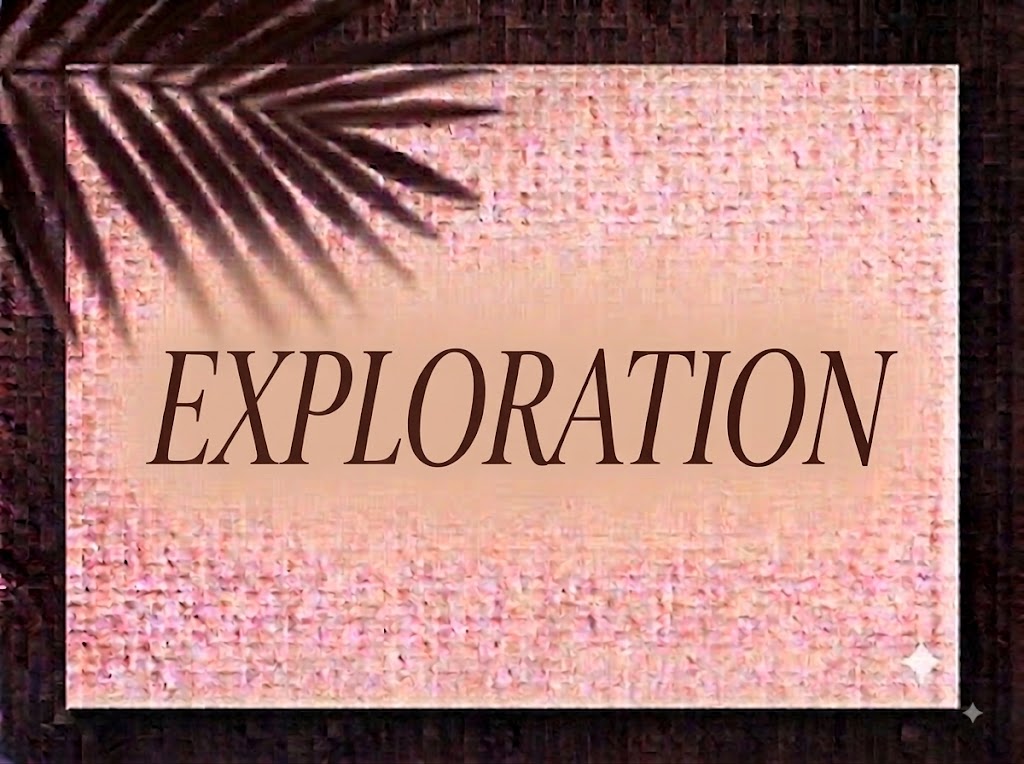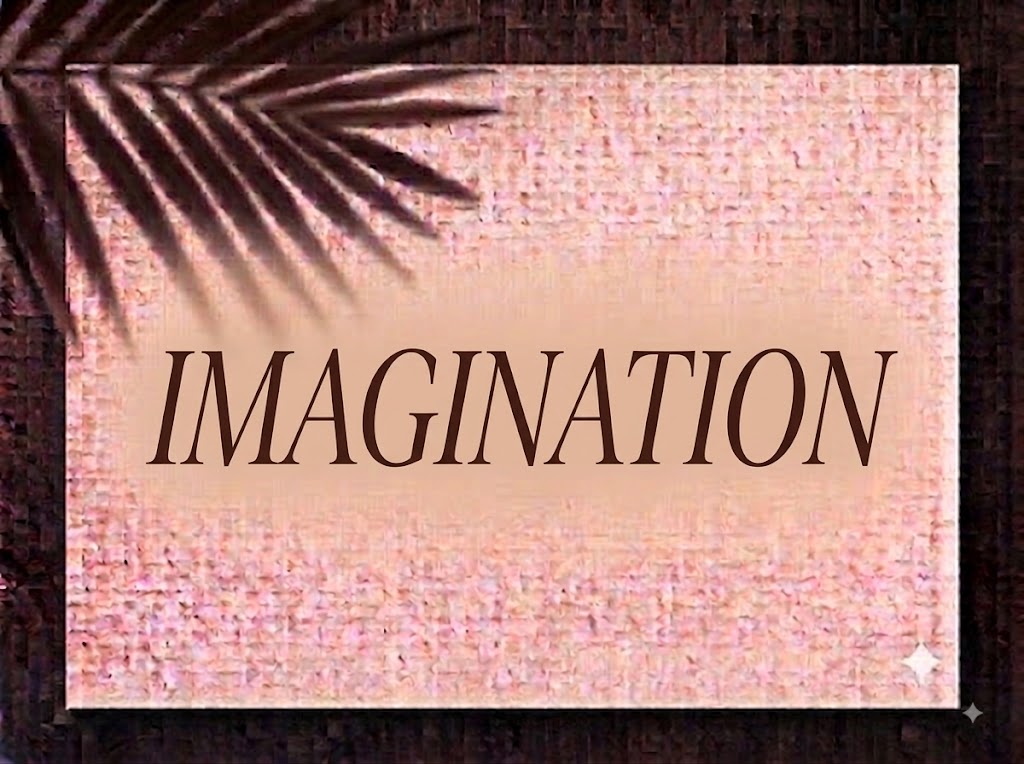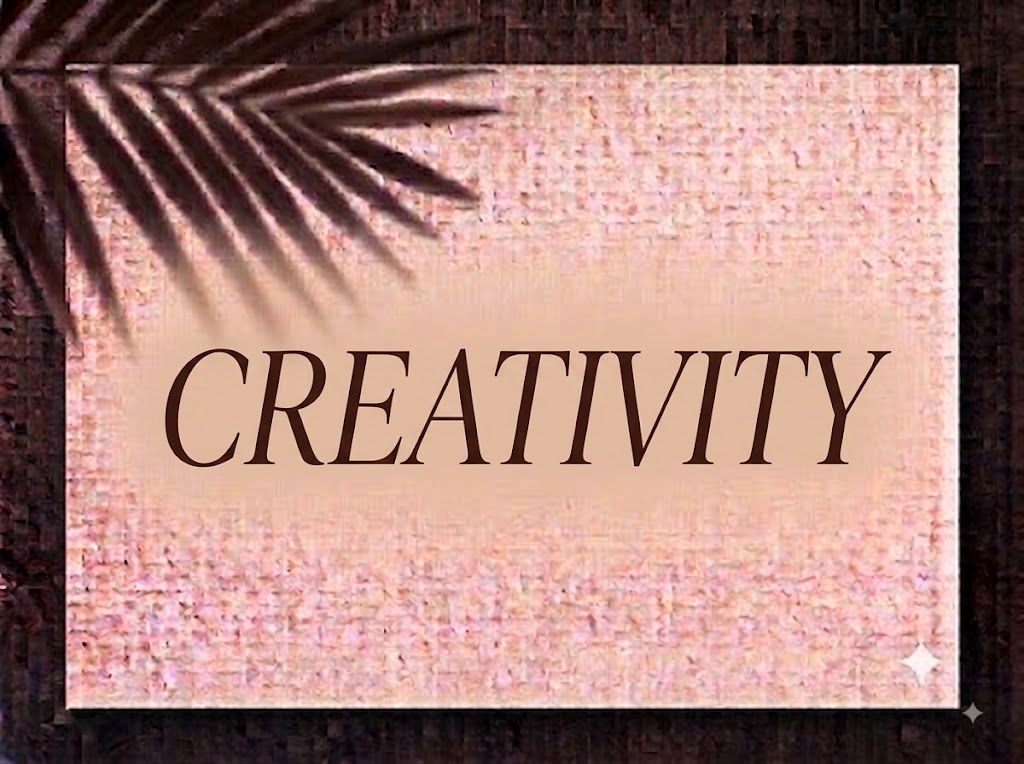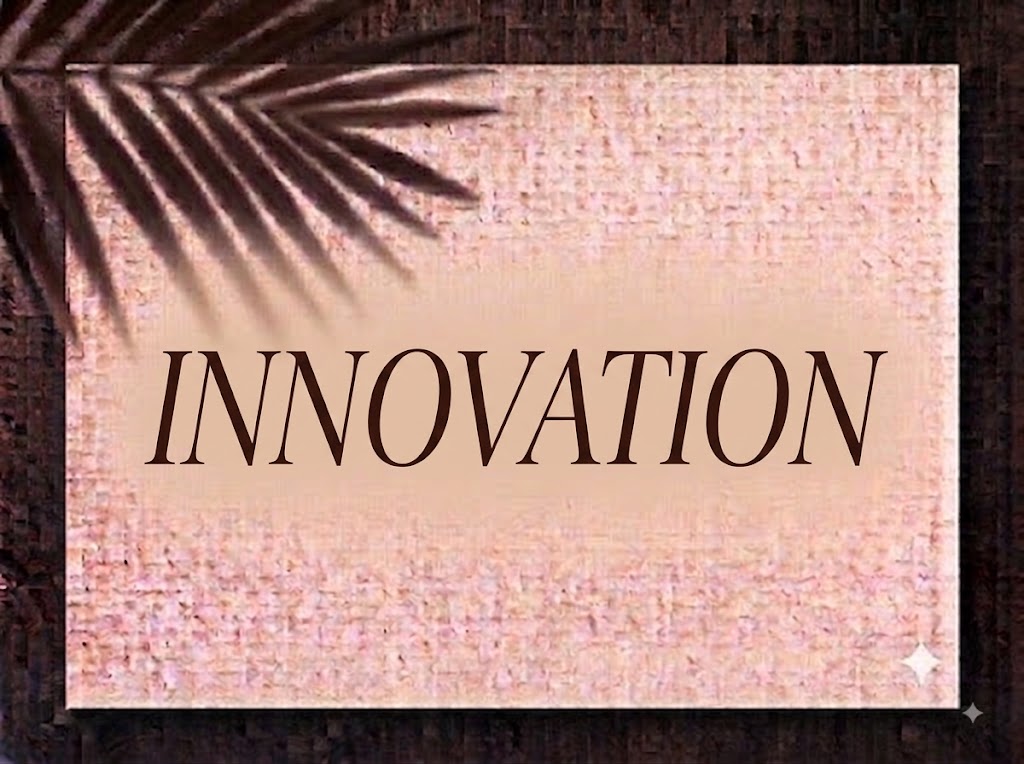
1FTV VIP Ameng
Trong ngành thiết kế đồ họa truyền thông cao cấp, thời trang và xuất bản Tạp chí (Editorial), những bộ chữ hiển thị (display serif) sở hữu đường nét kiêu sa cùng các chi tiết uốn biến điệu độc đáo luôn mang đến sức hút thị giác vượt trội. Một tiêu đề được trau chuốt tinh tế không chỉ truyền tải trọn vẹn thông điệp mà còn nâng tầm đẳng cấp nghệ thuật cho toàn bộ ấn phẩm.
Nếu bạn đang tìm kiếm một phông chữ Serif vừa thanh lịch, vừa phá cách với các nét vòng (loop) mềm mại ở các ký tự tiếng Việt để làm logo, bìa tạp chí, lookbook hay tiêu đề video ngắn, font 1FTV VIP Ameng chính là sự lựa chọn không thể bỏ qua.
Giới thiệu về font 1FTV VIP Ameng
Font 1FTV VIP Ameng là bộ chữ hiển thị có chân (display serif) mang phong cách tân cổ điển đầy tính nghệ thuật, nổi bật với sự kết hợp giữa nét chữ thanh thoát và các đường cong cách điệu độc bản:
Tên phông chữ: 1FTV VIP Ameng
Được hoàn thiện kỹ lưỡng về mặt kỹ thuật, phông chữ đem lại khả năng hiển thị vô cùng mượt mà. Bạn có thể tự tin phóng lớn tiêu đề trên các phần mềm thiết kế đồ họa chuyên nghiệp hay ứng dụng dựng video mà không lo gặp tình trạng vỡ nét hay dính nét.
Đặc điểm nổi bật của phong cách thiết kế VIP Ameng
Sức hút thị giác của font 1FTV VIP Ameng đến từ phom dáng quyến rũ cùng sự phá cách trong cấu trúc từng ký tự:
Chi tiết nét vòng (Loop Accents) nghệ thuật: Điểm đắt giá nhất của phông chữ nằm ở các nét cong uốn xoe tròn tinh tế ở các chữ cái như
g,y,e,o,v… Chi tiết này đem lại cảm giác kiều diễm, uyển chuyển như nét vẽ thủ công cao cấp. -
Tương phản thanh đậm tinh tế: Sự chênh lệch giữa cột nét dọc đứng dáng và các đường cong mỏng nhẹ tạo nên chiều sâu thị giác sang trọng, gợi liên tưởng đến các thương hiệu nước hoa, mỹ phẩm và thời trang xa xỉ.
Thiết kế Việt hóa chỉn chu: Các dấu thanh tiếng Việt (sắc, huyền, hỏi, ngã, nặng) và dấu mũ được tạo hình gọn gàng, đặt vị trí chuẩn xác giúp văn bản tiếng Việt giữ nguyên tinh thần thanh lịch mà không bị rồi mắt.
Khoảng cách giữa các chữ (kerning) và độ giãn dòng được tính toán chuẩn xác, giúp các đường nét uốn lượn khi đứng cạnh nhau không bị dính hay đè nét.
Tích hợp trọn vẹn bộ chữ cái hoa – thường, dãy chữ số 0-9 phom dáng thanh lịch cùng hệ thống ký tự đặc biệt, dấu câu thông dụng.
Bản Việt hóa chuẩn chỉnh giúp bạn hoàn toàn yên tâm thiết kế các văn bản tiếng Việt có dấu phức tạp mà không gặp lỗi nhảy font hay mất ký tự.
Hình ảnh demo thực tế của font 1FTV VIP Ameng
Khả năng hiển thị của phông chữ này được tối ưu rất tốt trên nhiều tỷ lệ kích thước khác nhau:
Kích thước nhỏ (12pt – 24pt): Cấu trúc nét chữ rành mạch giúp câu chữ tiếng Việt vẫn hiển thị rõ ràng, sắc nét trên màn hình di động.
Kích thước lớn (36pt – 72pt): Đây là đất diễn lý tưởng nhất để 1FTV VIP Ameng phô diễn toàn bộ sự kiêu sa, sang trọng của các đường uốn nét nghệ thuật, tạo tác động thị giác mạnh mẽ cho các dòng tiêu đề chính.
Ứng dụng trong thiết kế đồ họa và làm video
Sở hữu nét cá tính kiều diễm và giàu nghệ thuật, font 1FTV VIP Ameng mở ra không gian ứng dụng phong phú:
Video ngắn (TikTok, Reels, Shorts): Dáng chữ Serif thanh lịch này hiển thị rất thu hút trên khung hình đứng tỷ lệ 9:16. Cực kỳ ăn nhập với các video vlog thời trang, review mỹ phẩm, trang sức, spa hay phong cách sống nghệ thuật.
Ảnh thu nhỏ YouTube (Thumbnail): Lựa chọn tuyệt vời cho các kênh làm nội dung về thời trang, làm đẹp, âm nhạc lofi, acoustic hoặc review đồ hiệu nhờ giao diện chuyên nghiệp và bắt mắt.
Thiết kế Bìa Tạp chí, Lookbook và Poster: Hoàn hảo cho các sản phẩm truyền thông thuộc lĩnh vực thời trang thiết kế, spa, mỹ phẩm, triển lãm nghệ thuật hay thương hiệu váy cưới.
Nhận diện thương hiệu phân khúc Luxury: Thích hợp làm logo dạng chữ, bao bì nước hoa, menu nhà hàng/khách sạn 5 sao hay thiệp mời sự kiện VIP.